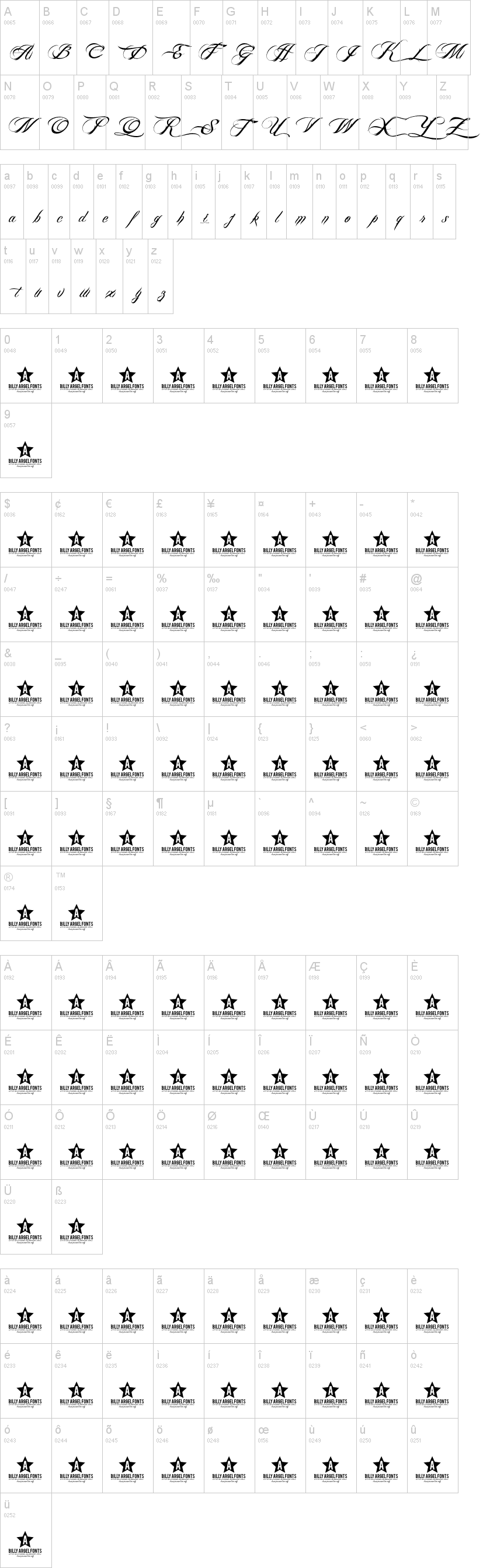
Billy Argel Font
Billy Argel Font 是一款具有经典设计风格的英文字体,它由著名的西班牙设计师Billy Argel创作。它的字体形状简洁,笔画细腻,体现出浓浓的古典风格,十分精致。它具有优秀的可读性,可以用于各种文字设计,尤其适合用于书籍封面、海报、标识、标题等设计中。
Billy Argel Font是一款非常不错的手写艺术字体,具有很好的视觉感,适合于文化类的宣传设计、商业类品牌的广告和产品包装设计以及个性化文字排版等较多场景。